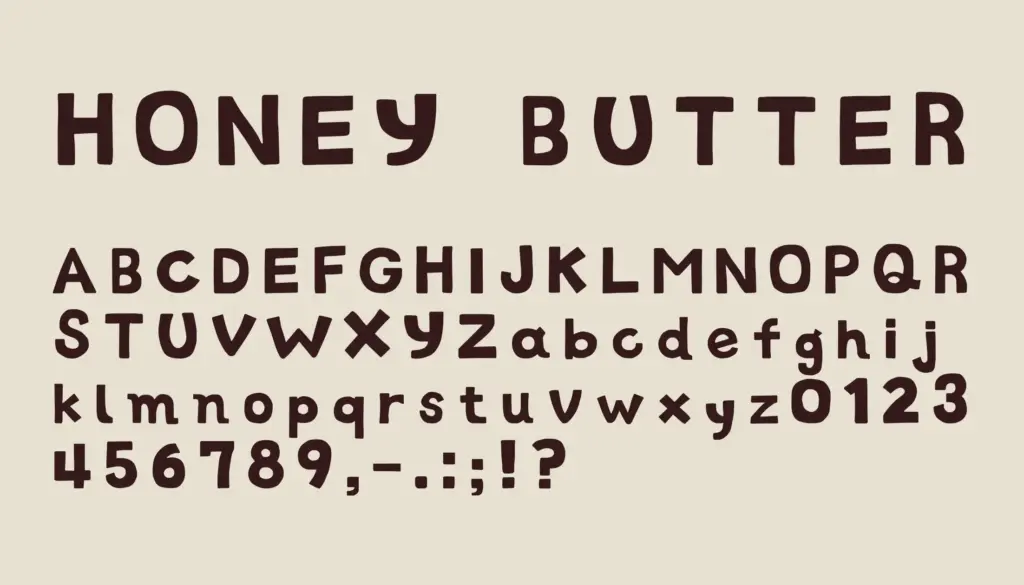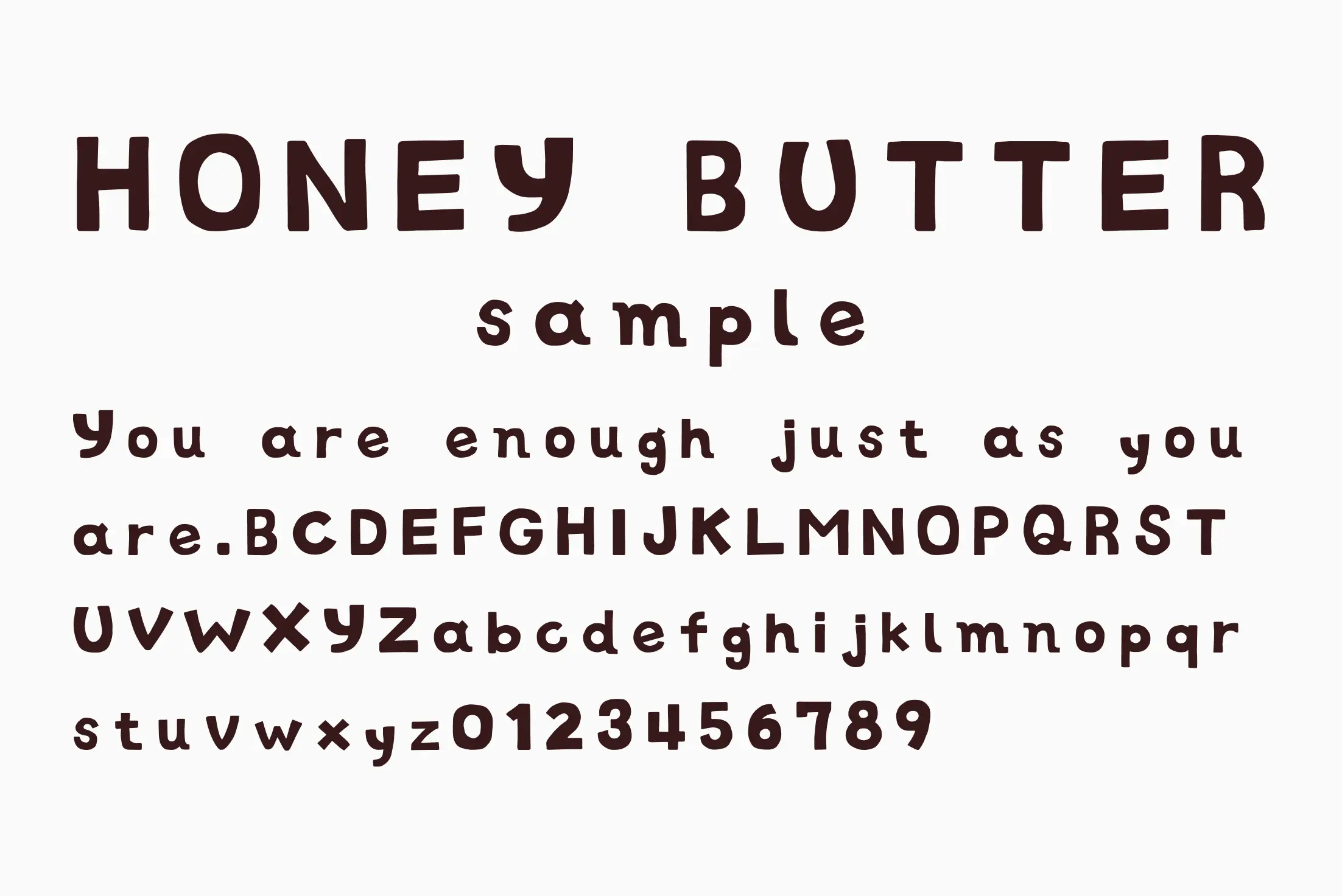
太くて丸みを帯びたデザインが特徴の英字フォントです。柔らかさとインパクトを兼ね備えており、スイーツやカフェのメニュー、ポップなデザインにぴったり。YouTubeのサムネイルやSNS投稿、雑貨やスイーツブランドのロゴなど、親しみやすくて視覚的にかわいい雰囲気を作りたいときに活躍します。
HONEY BUTTER